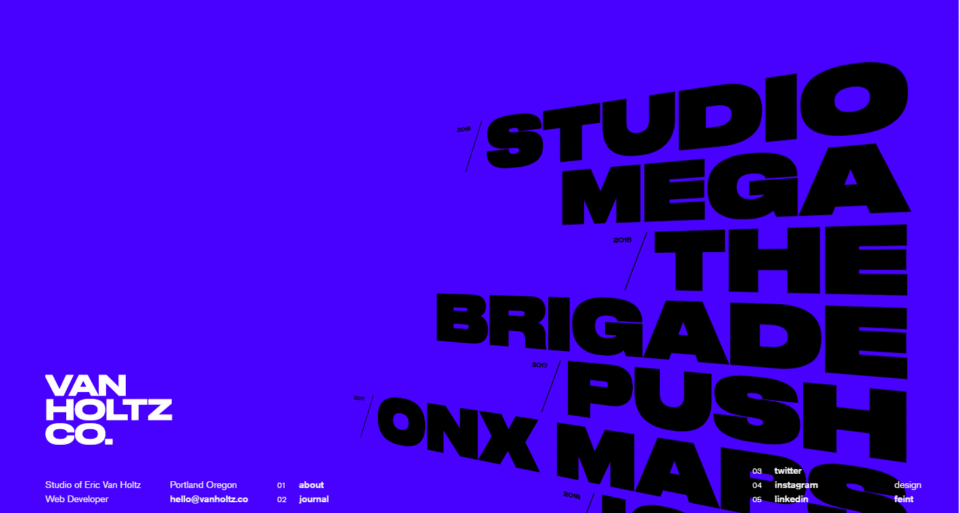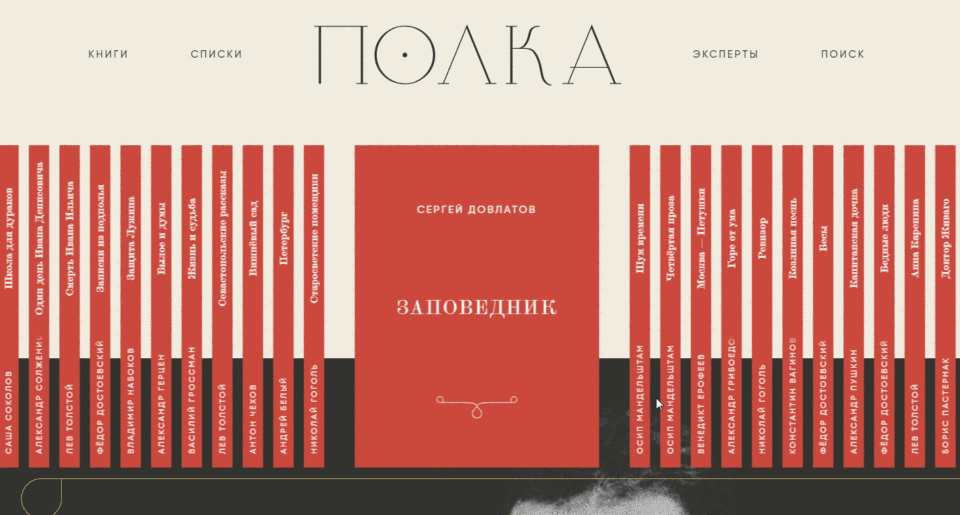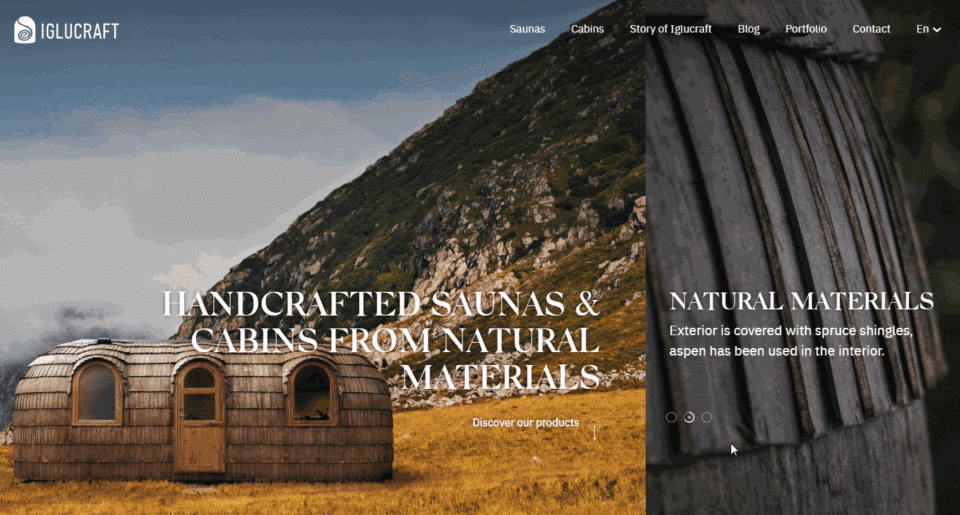
17 trang web hướng dẫn thiết kế typography tốt nhất để tạo trang web nổi bật
17 trang web hướng dẫn thiết kế typography và phông chữ miễn phí tuyệt vời sẽ được giới thiệu để giúp bạn có thiết kế kiểu chữ tốt nhất cho trang web.  “Hơn 95% phần trăm thông tin trên web là ở dạng ngôn ngữ viết” Oliver Reichenstein
Typography tốt đem lại khả năng đọc, hiệu ứng hình ảnh, bố cục tốt hơn, làm cho một trang web hấp dẫn hơn và cung cấp một UX tốt hơn. Đây là lý do tại sao ngày càng nhiều nhà thiết kế chú ý nhiều hơn đến thiết kế Typography cho web.
Hôm nay, chúng tôi tập trung vào typography. Chúng tôi đã thu thập 17 trang web hướng dẫn thiết kế typography tốt nhất,  và 10 font chữ typography miễn phí tốt nhất sẽ giúp bạn tạo ra các trang web nổi bật:
Pittori Di Cinema
Điểm nổi bật: Phong cách thiết kế typography rất lớn
Phong cách thiết kế typography làm thiết kế website trong bắt mắt hơn và nổi bật nội dung web một cách hiệu quả. Đó là lý do tại sao nó đã trở thành một trong những xu hướng thiết kế typography cho web phổ biến nhất trong số các thiết kế vào những năm gần đây. Trang web một trang theo xu hướng thiết kế này và sử dụng các kiểu chữ rất lớn để thu hút sự chú ý của người dùng và cung cấp thông tin web.
Các font chữ cá nhân và bảng màu tạo ra sự hấp dẫn thị giác đáng chú ý.
Bạn có thể học được gì:
Tối ưu hóa trang web của bạn với typography lớn
Kiểu chữ càng lớn, trang web của bạn sẽ càng bắt mắt. Vì vậy, đó là một ý tưởng tốt để sử dụng phong cách thiết kế typography lớn trong thiết kế web của bạn. Cũng trang trí thiết kế typography lớn của bạn với các biểu tượng, biểu tượng cảm xúc, độ tương phản màu sắc và hiệu ứng động, v.v.
Noaka
Điểm nổi bật: Thiết kế kiểu kệ sách đời thực
Với mục tiêu giúp người dùng tìm thấy những cuốn sách họ cần, trang web này được sáng tạo với thiết kế kiểu kệ sách thực tế đáng chú ý bằng cách sử dụng typography dọc độc đáo và nghệ thuật. Người dùng có thể dễ dàng nhấp vào văn bản dọc để kiểm tra chi tiết sách và chuyển sang sách khác.
Bạn có thể học được gì:
Tạo một typography và bố cục web độc đáo kết hợp với các chủ đề trang web và các tính năng sản phẩm
Iglucraft
Điểm nổi bật: Hình ảnh kết hợp với văn bản
Typography rực rỡ kết hợp với hình ảnh đẹp và chất lượng cao luôn là một sự kết hợp chiến thắng. Thiết kế trang web thương mại điện tử này tuân theo ý tưởng thiết kế và sử dụng các cặp văn bản với ảnh hoàn hảo cho người dùng để hiển thị nét nổi bật của từng sản phẩm.
Bạn có thể học được gì:
Ghép văn bản với hình ảnh phù hợp
QWIC
Điểm nổi bật: Typography nổi bật trong bố trí lưới
Trang web thương mại điện tử này sử dụng các lưới để phân chia trang web thành nhiều khu vực chức năng cũng như làm cho văn bản và các cặp ảnh rõ ràng, trực quan hơn để người dùng nhanh chóng tìm thấy thông tin cần thiết.
Bạn có thể học được gì:
Tối ưu hóa typographyvà bố cục trang web của bạn với lưới
Cambridge International School
Điểm nổi bật: Điều hướng sáng tạo
Là trang web chính thức của Cambridge International School ở  Nga, trang web giáo dục này sử dụng điều hướng từng bước sáng tạo và chức năng để thu hút người dùng. Thiết kế typography của nó bao gồm các văn bản trong các kích cỡ khác nhau. Đây là một ví dụ tốt để bạn làm theo.
Bạn có thể học được gì:
Thiết kế typography cho trang web của bạn với các nút, menu web và hệ thống điều hướng để làm cho nó hoạt động
Reflektor Digital Website
Điểm nổi bật: Công nghệ 3D; Hiệu ứng chất lỏng và phát sáng; Âm thanh
Trang web của đơn vị thiết kế này có phong cách khoa học viễn tưởng bằng cách sử dụng font chữ độc đáo, công nghệ 3D, hiệu ứng mượt mà và phát sáng. Các thiết kế tương tác và âm thanh nhúng tạo ra một trải nghiệm tiên tiến và nghệ thuật.
Eleven Plants for Dum Dums
Điểm nổi bật: Thiết kế typography phân cấp
Sử dụng các văn bản thuần túy là một trong những phương pháp hiệu quả nhất cho các nhà thiết kế để tạo ra một trang web tối giản tuyệt vời. Trang web của nhà máy áp dụng phương pháp này tạo ra một typography phân cấp tuyệt đẹp bằng cách sử dụng các từ trong các font chữ, kích cỡ và màu sắc khác nhau.
Bạn có thể học được gì:
Thiết kế typography phân cấp cho trang web của bạn bằng cách sử dụng các văn bản theo nhiều font chữ, kích cỡ, màu sắc và kiểu dáng,
BuzzworthyStudio
Chúng tôi hy vọng 17 trang web typography tuyệt vời này,  và font chữ typography miễn phí này sẽ giúp bạn tạo ra trang web nổi bật.